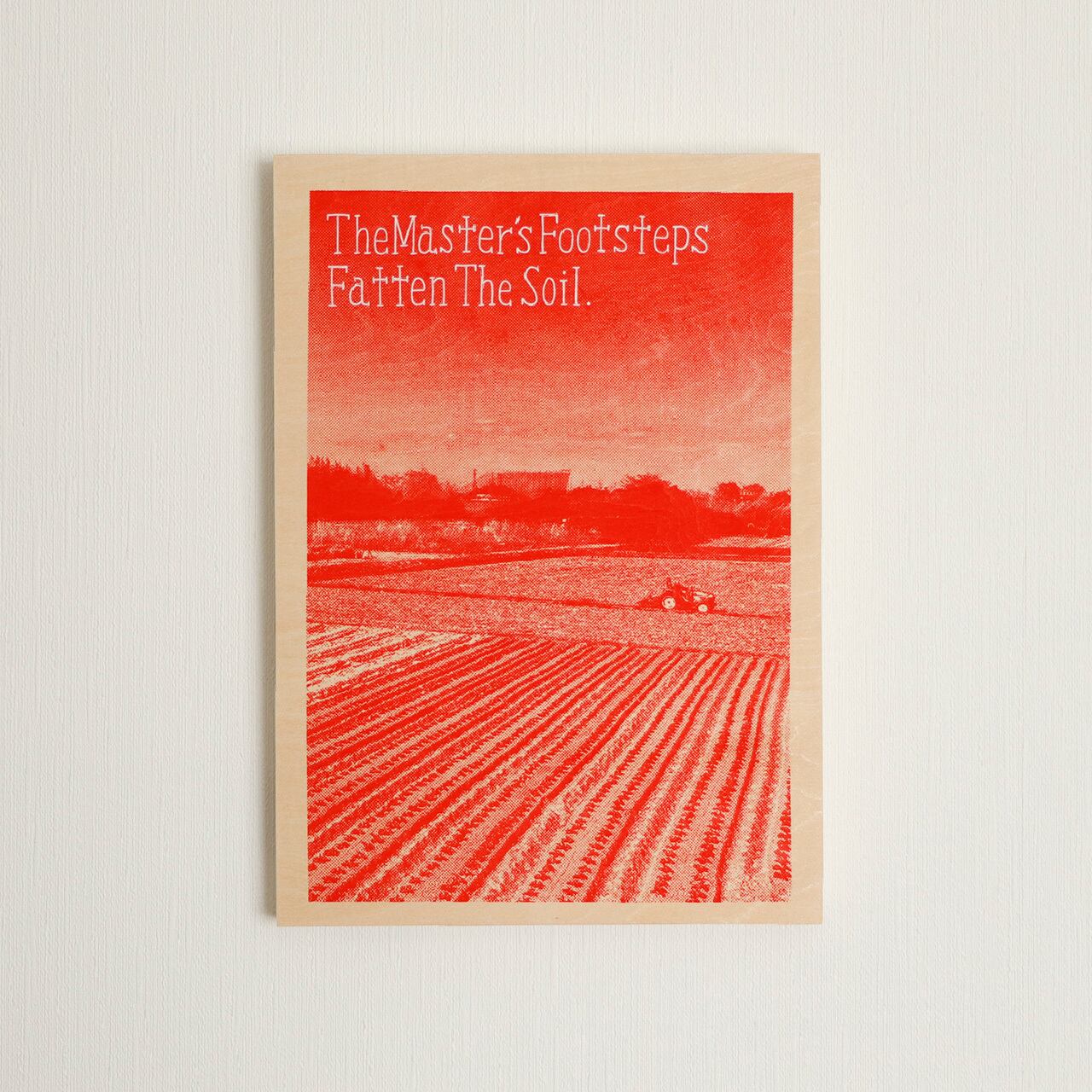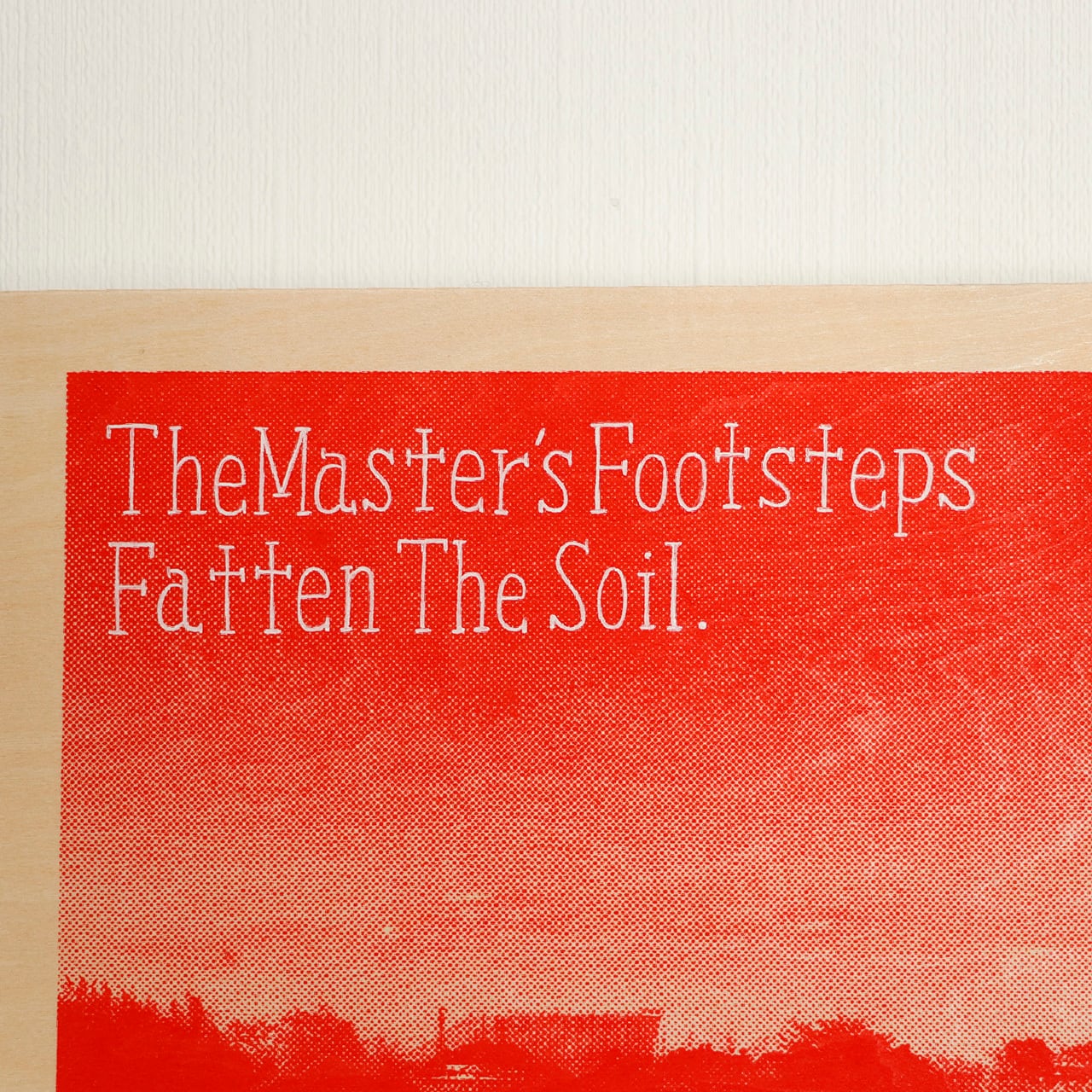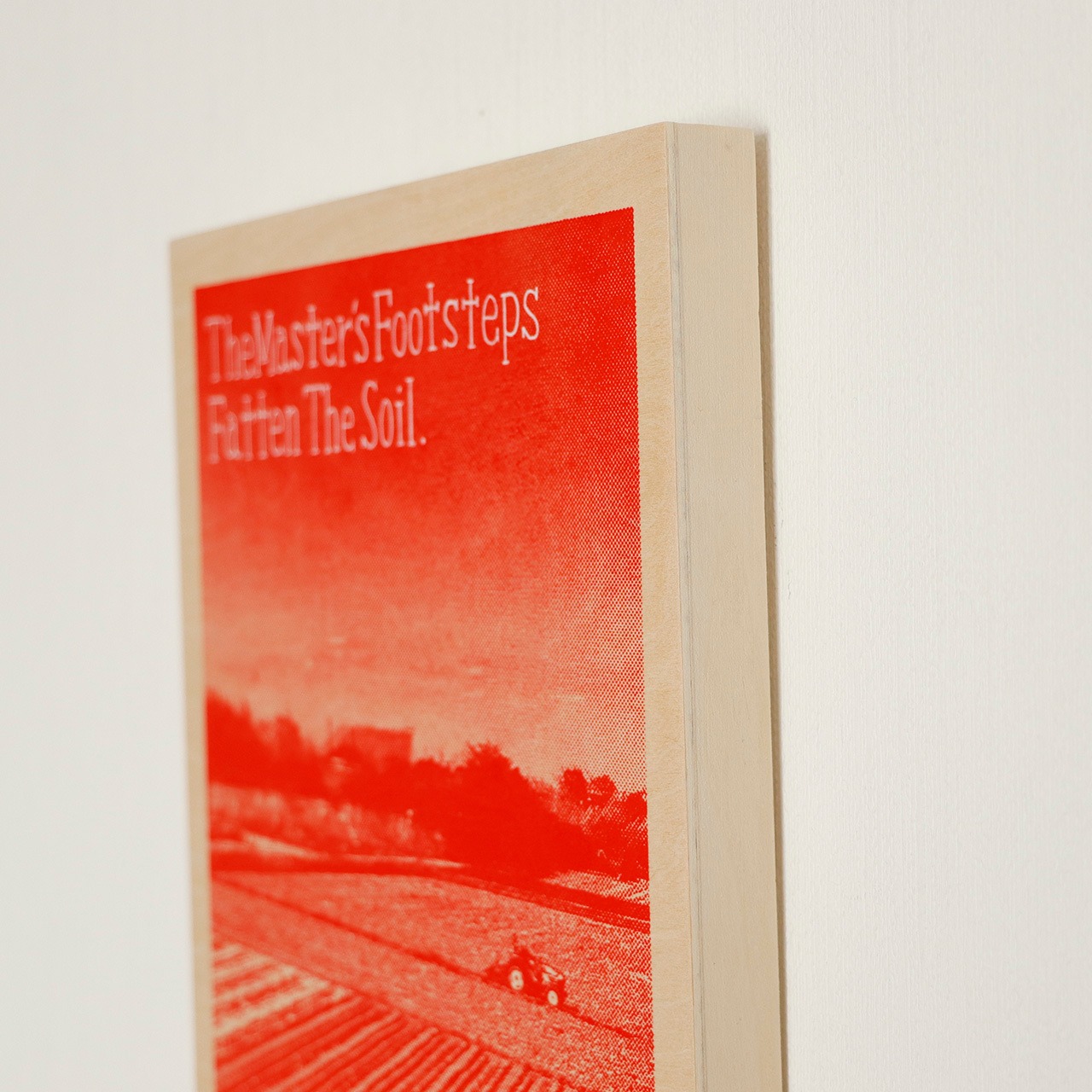
The master’s footsteps fatten the soil / red
The master’s footsteps fatten the soil
主人の足跡が土を肥やす
地に足をつけて進みたい時に。足跡が着実に力や経験になります。
広大な畑を一人トラクターで耕しているところが素敵だったので、この言葉を選びました。
木の板に写真をシルクスクリーン印刷、油性ペンで文字を描いています。